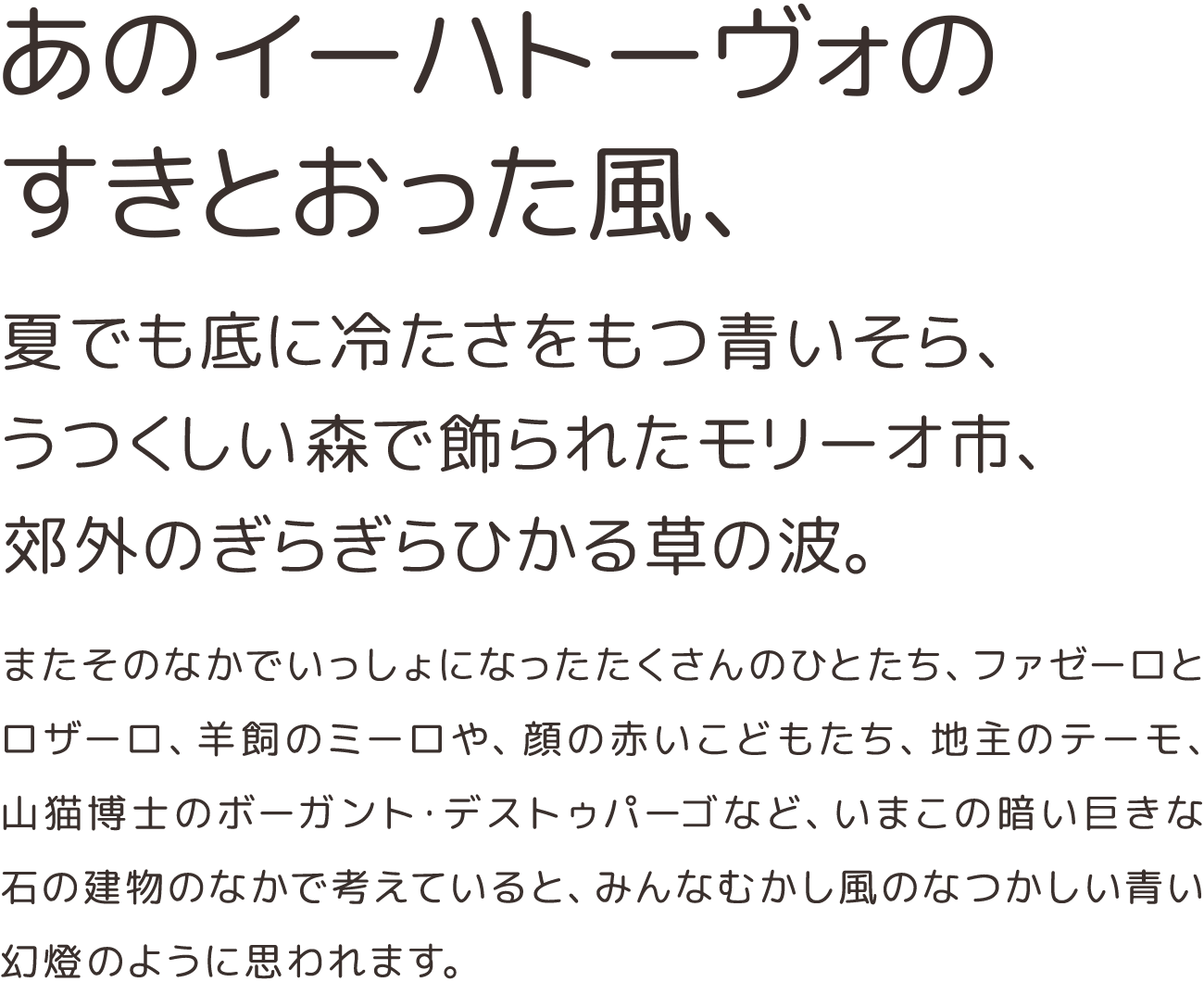
M PLUS Rounded 1c Regular
エンタメ系や子ども向けのデザインでよく使われている、やさしくて楽しげな丸ゴシック体のフォント。7ウエイト展開で、Webフォントとしても無料・PV数無制限で使用可能。
本文はゴシック体の「M PLUS 1p」にするなど、組み合わせて使うのもおすすめ!